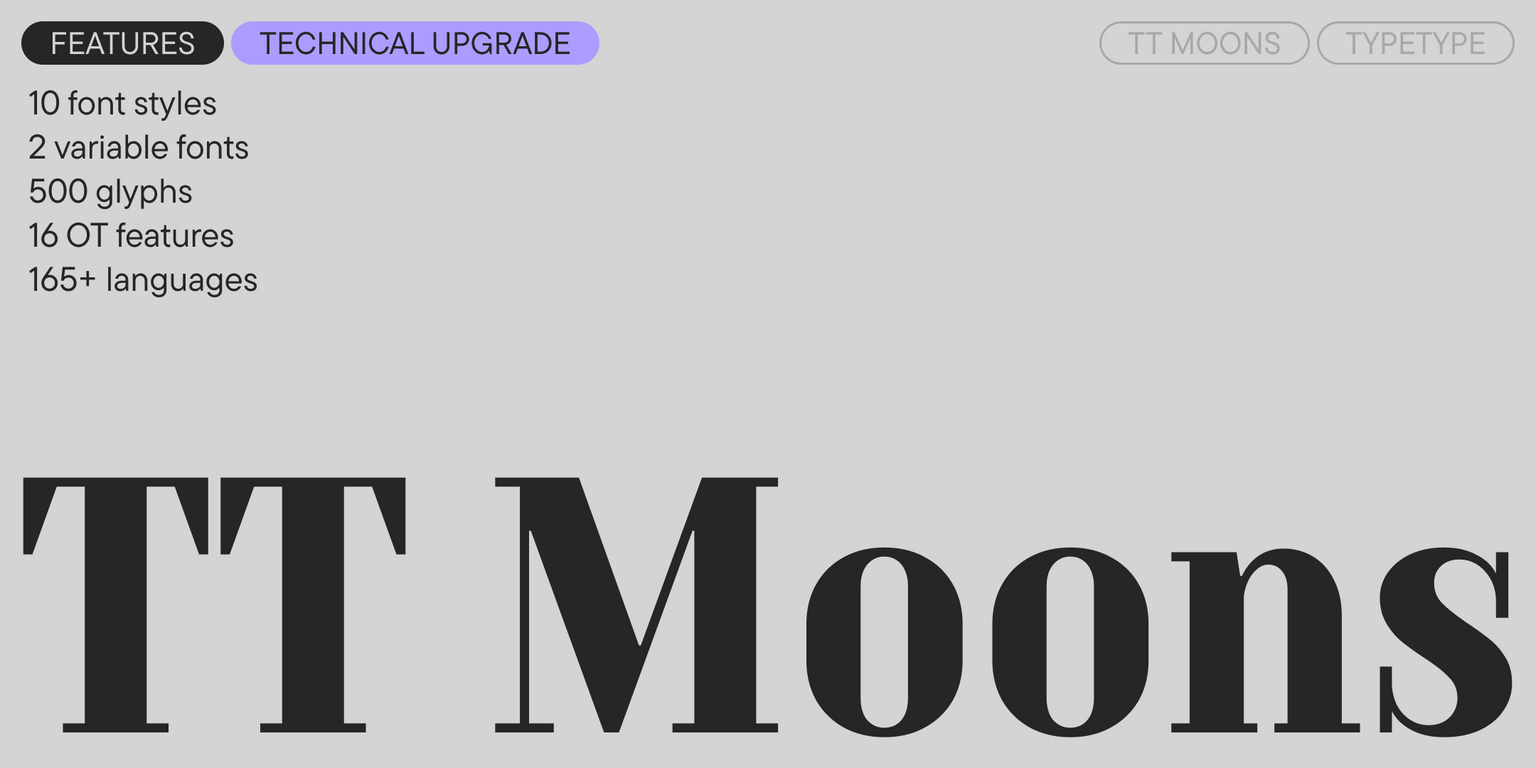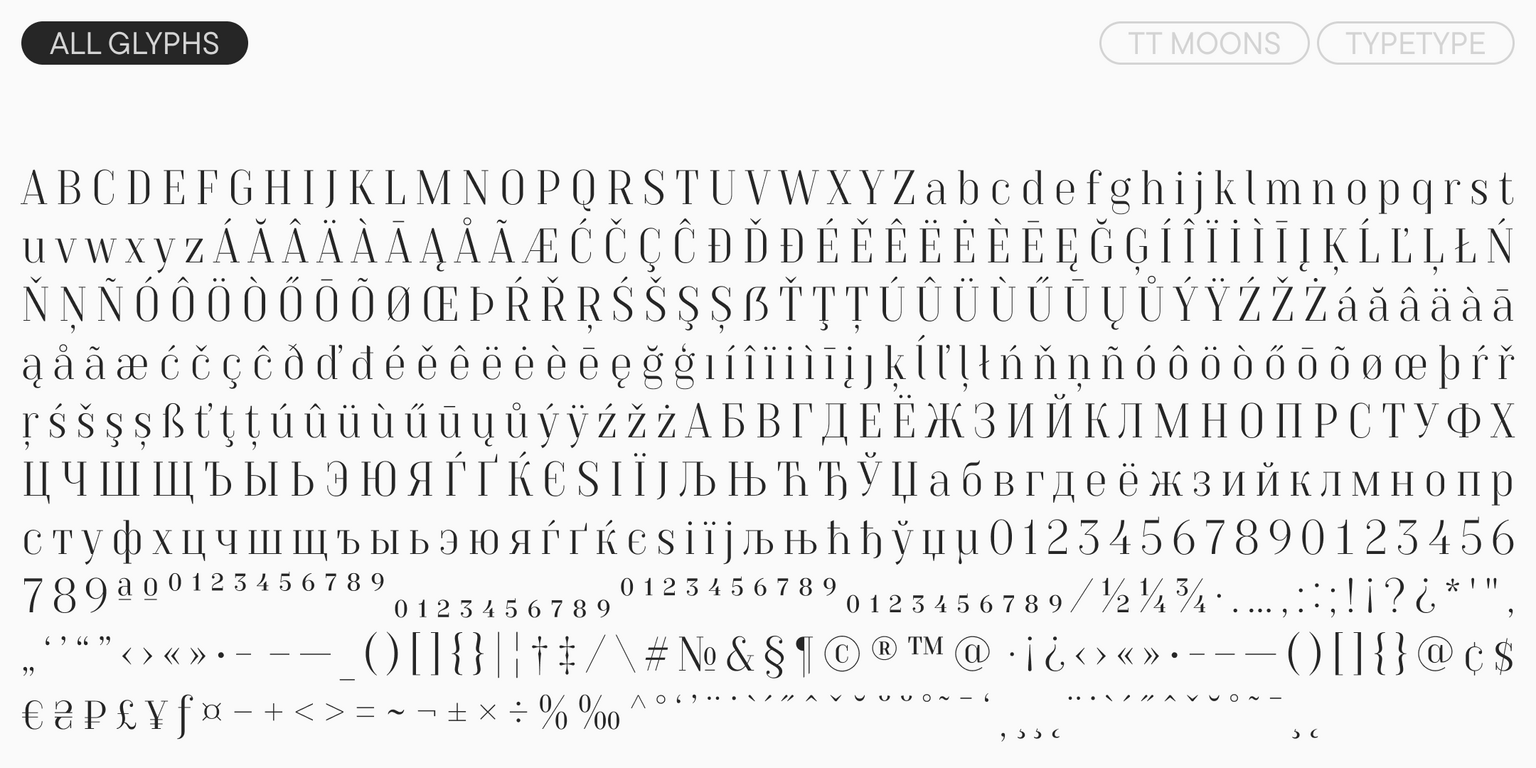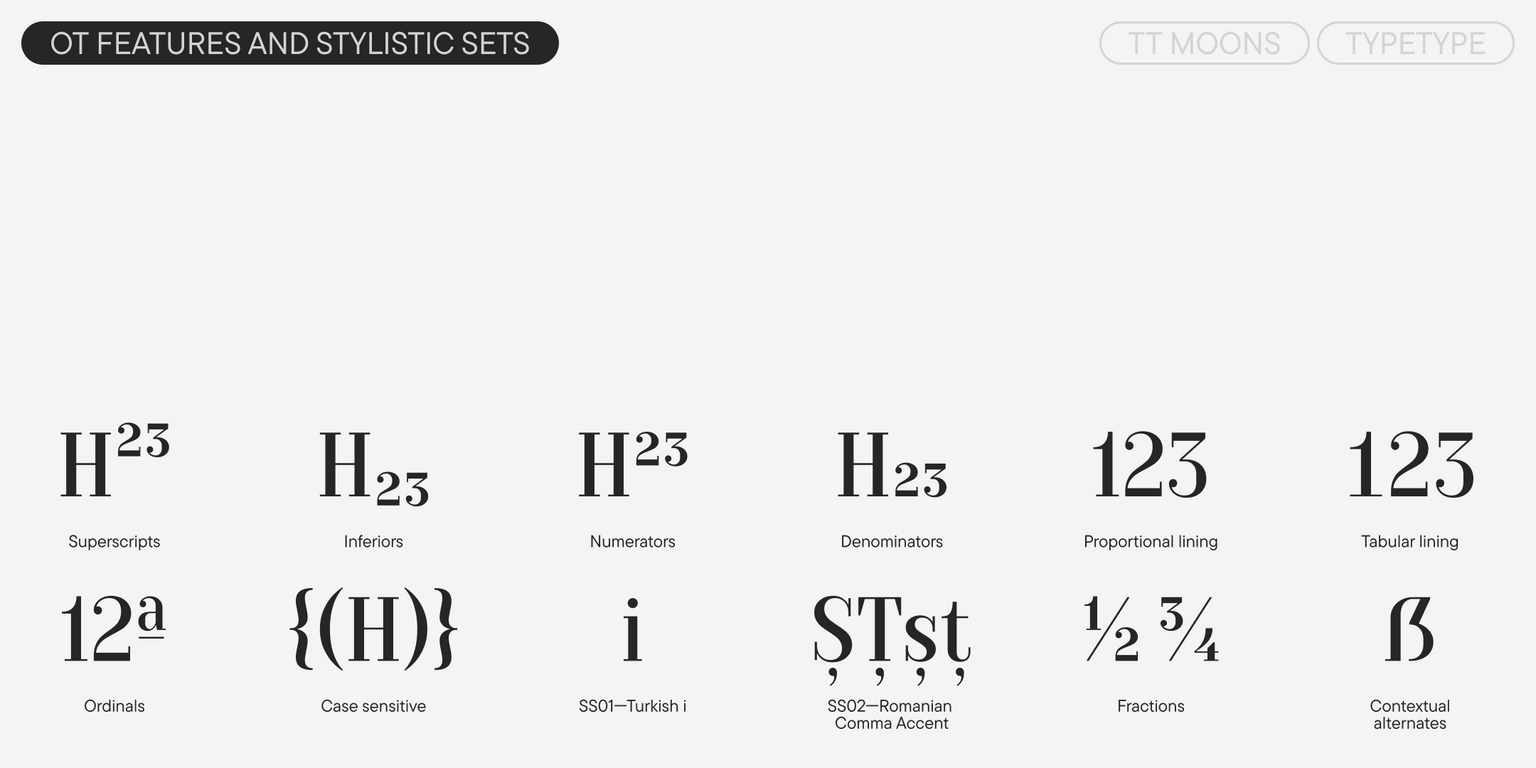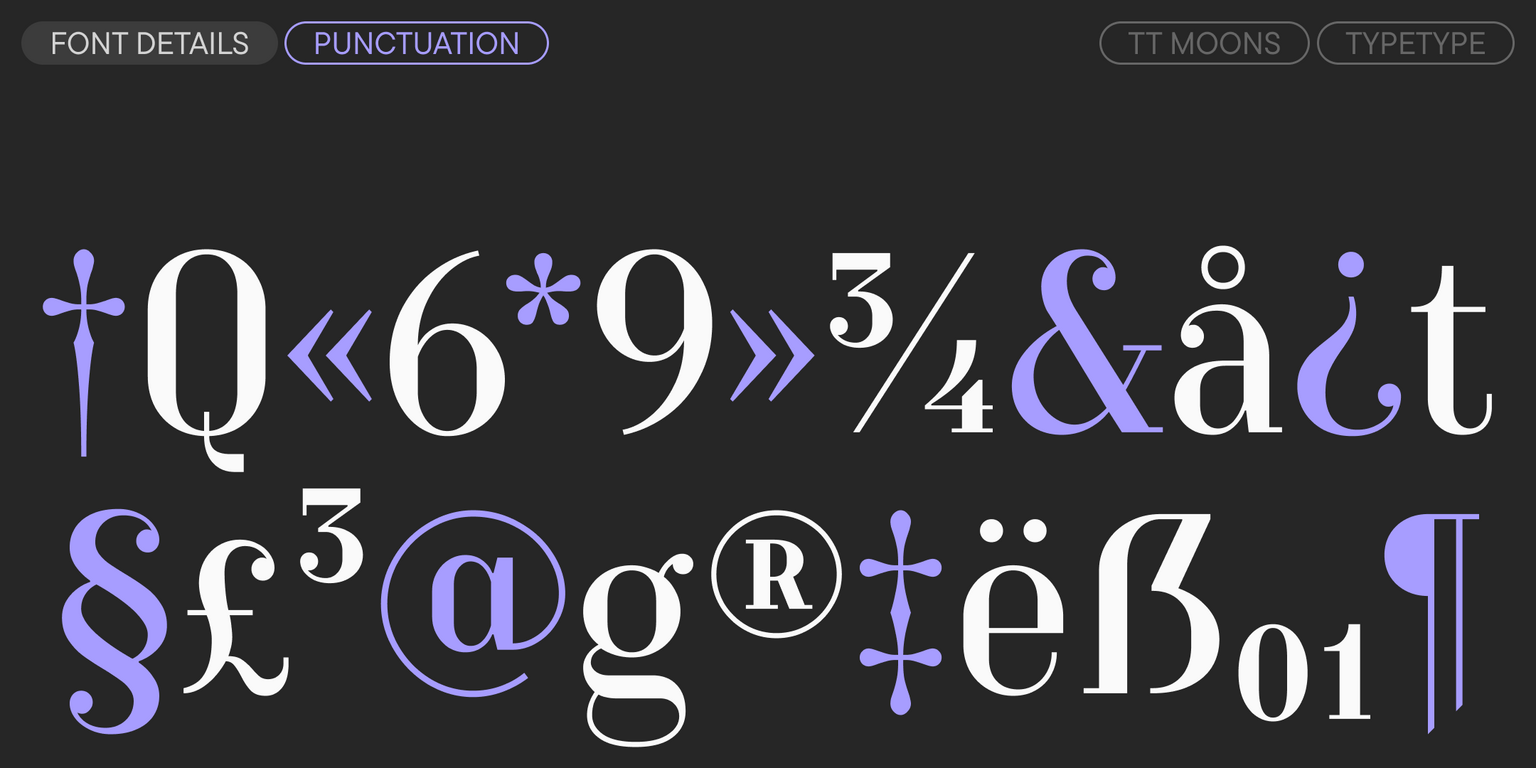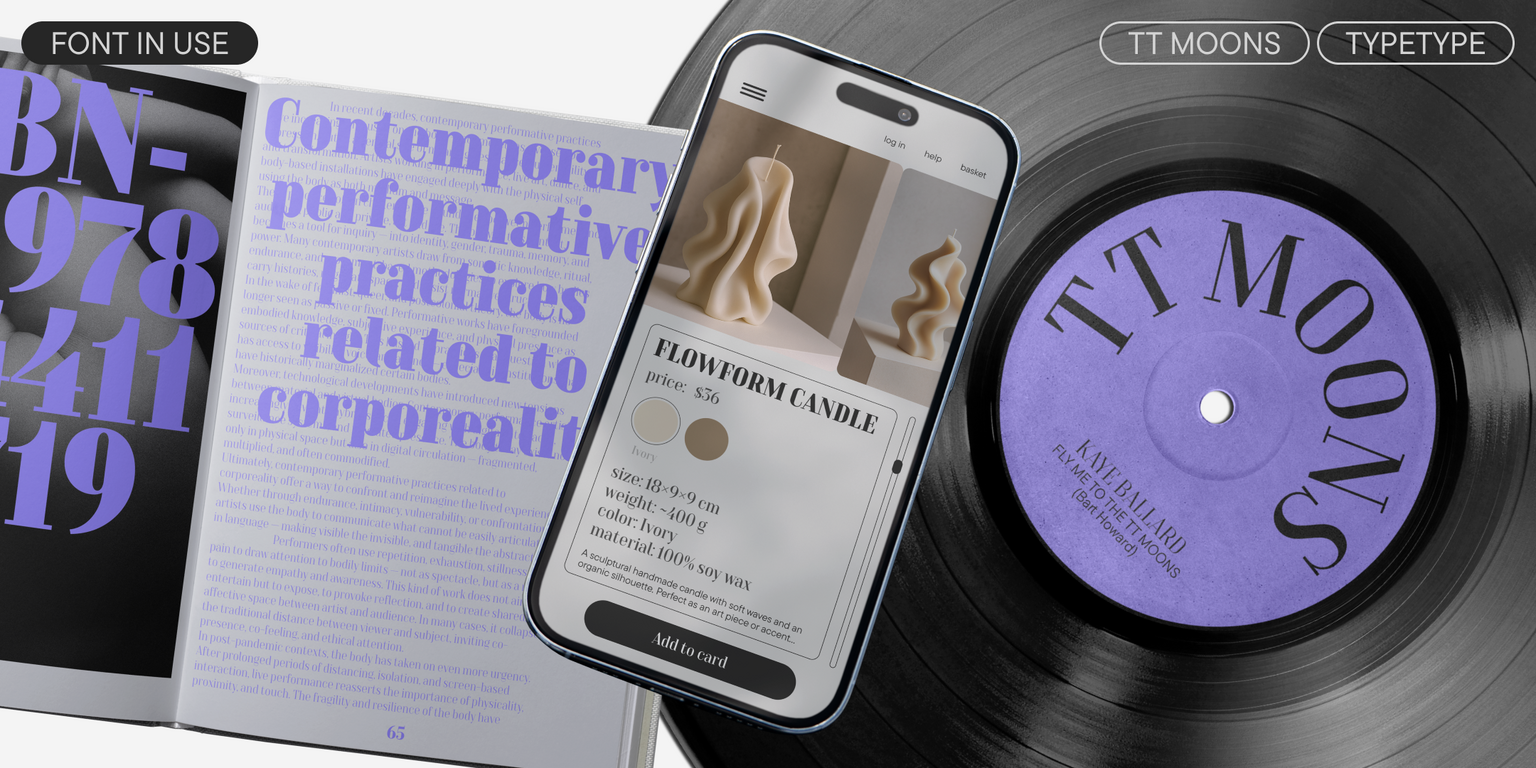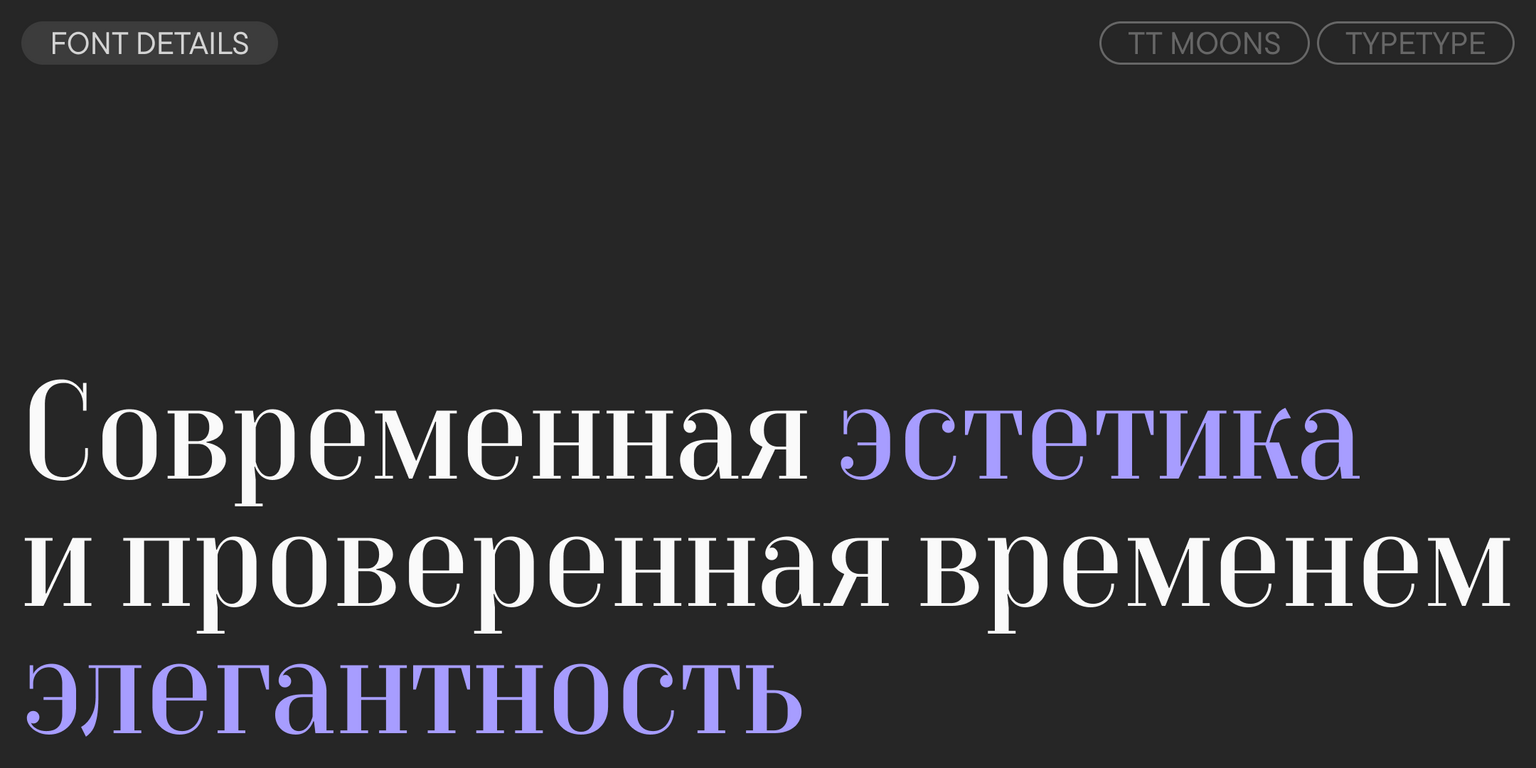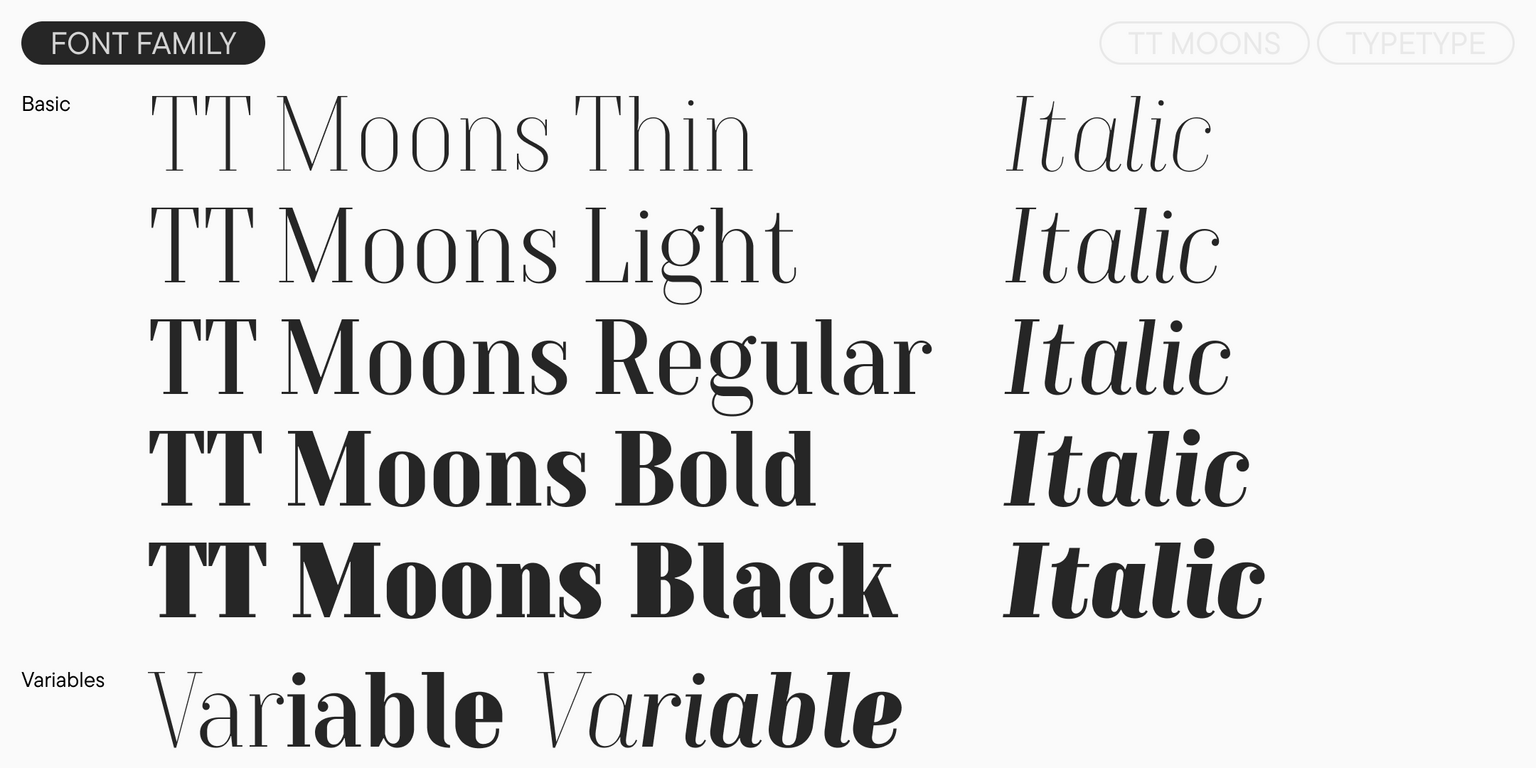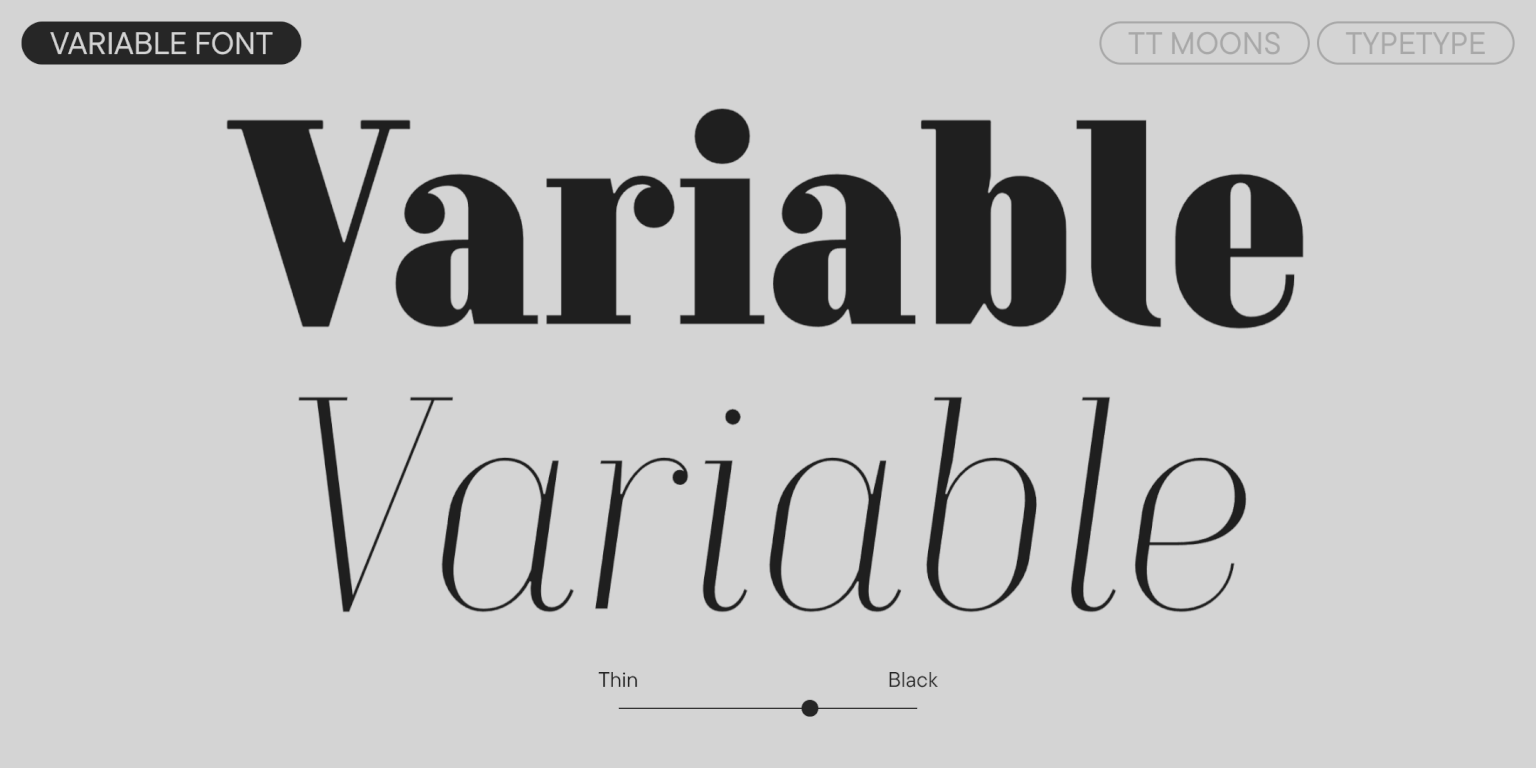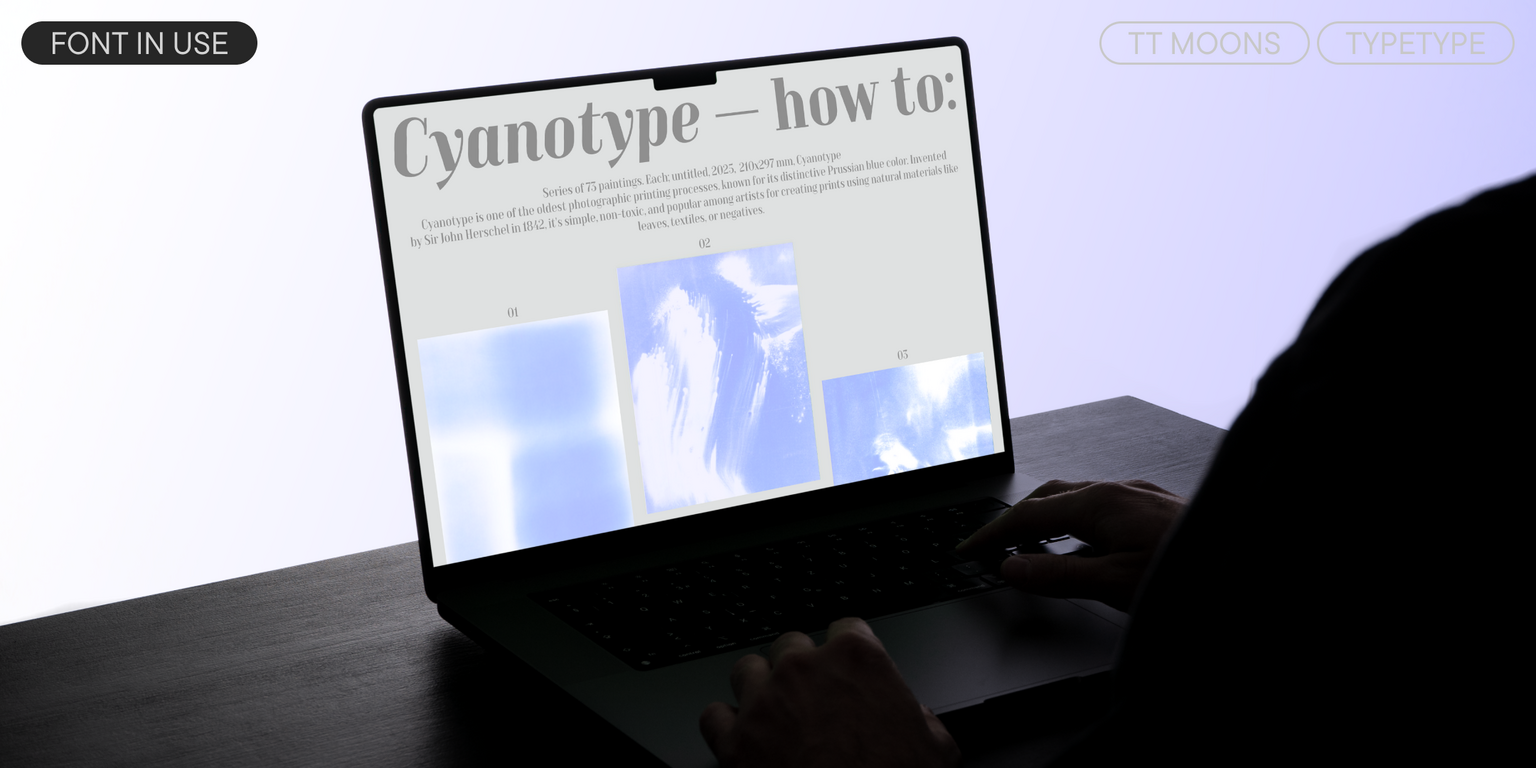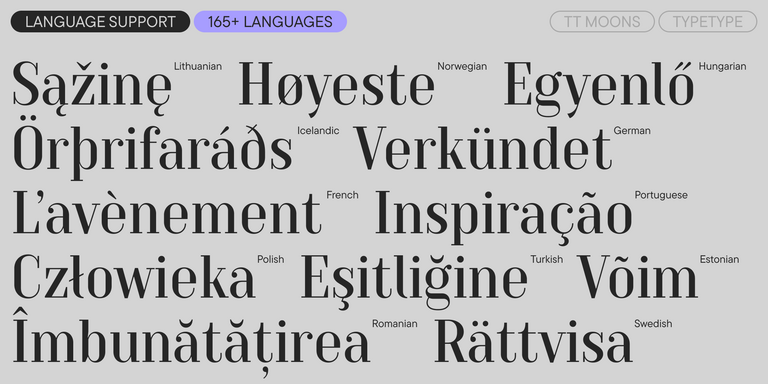
TT Moons
TT Moons — ТТ Мунс
Произносится «ТТ Мунс». «Moons» — производное слово от Moon, в переводе с английского «Луна». Буквы «TT» являются аббревиатурой названия компании.
TT Moons — контрастная антиква с узкими пропорциями. Идеальная сфера использования этого шрифта — вёрстка журналов, книг и газет.
TT Moons: элегантная новостильная антиква
TT Moons представляет собой узкую контрастную антикву, выполненную в лучших традициях глиптальных новостильных шрифтов с засечками. Её утончённые пропорции, элегантные засечки и продуманные детали создают гармоничный ритм, который особенно ценится в качественной типографике. Классический характер этого шрифтового семейства делает его идеальным выбором для сложной текстовой работы — будь то вёрстка литературных изданий, оформление художественных альбомов или дизайн престижных журналов. Гармоничное сочетание традиционных форм с современной проработкой деталей позволяет TT Moons одинаково успешно работать как в печатной, так и в цифровой среде. Пять тщательно сбалансированных начертаний — от лёгкого (Thin) до жирного (Black) — предоставляют дизайнеру широкие возможности для создания выразительной типографической иерархии (структуры). Благодаря своей универсальности, шрифт находит применение в корпоративных коммуникациях, цифровых продуктах, издательском деле и рекламных проектах, где требуется сочетать проверенную временем элегантность с современной визуальной эстетикой.
Сфера использования: полиграфия, интерфейсы, айдентика
В 2025 году добавилось два вариативных шрифта
О гарнитуре TT Moons
Поддержка языков 160+
Встречайте обновлённый TT Moons версии 1.200!
Расширили кассовый состав, усовершенствовали шрифт технически, добавили новые функции и вариативные начертания.
TT Moons — элегантная новостильная антиква с узкими пропорциями, выраженным контрастом и гармоничным ритмом. Традиционные формы в ней сочетаются с современными деталями. Благодаря этим особенностям рисунок шрифта отсылает к классике, но при этом выглядит свежо и актуально.
В гарнитуру входит пять начертаний разных толщин и соответствующие им италики. В обновлённую версию мы добавили новые знаки и OpenType фичи для большей функциональности, а также два вариативных шрифта, меняющихся по оси жирности — для прямого и наклонного весов. Кроме того, мы провели детальную ручную ревизию кернинга и добавили ручной хинтинг для всех начертаний.
Идеальная сфера использования TT Moons — вёрстка журналов, книг и газет. Этот шрифт лучше всего проявляет себя в крупном или среднем размере. Он одинаково хорошо работает в печати и вебе, может стать частью корпоративного или продуктового дизайна, использоваться в оформлении афиш или вывесок. Гарнитура станет отличным помощником в случаях, когда нужно сочетать классику и современность.
TT Moons 1.200 — это:
• 12 начертаний: 5 прямых, 5 наклонных и два вариативных шрифта;
• 500 знаков в каждом начертании;
• 16 OpenType фич;
• Поддержка 165 языков.
TT Moons — элегантность вне времени!
Что изменилось в шрифте:
• Добавилось два вариативных начертания: для прямого и наклонного весов. Общее количество начертаний выросло с 10 до 12;
• Количество знаков в каждом начертании выросло с 490 до 500;
• Количество OpenType фич выросло с 10 до 16;
• Мы провели детальную ручную ревизию кернинга во всех начертаниях;
• Добавили ручной хинтинг для всех начертаний;
• Пересобрали шрифт из формата Fontlab 5 в формат Glyphs.
ss01 ӏ Romanian Comma Accent
tnum | Tabular Figures
numr | Numerator
dnom | Denominator
sups | Superscript
sinf | Scientific Inferiors